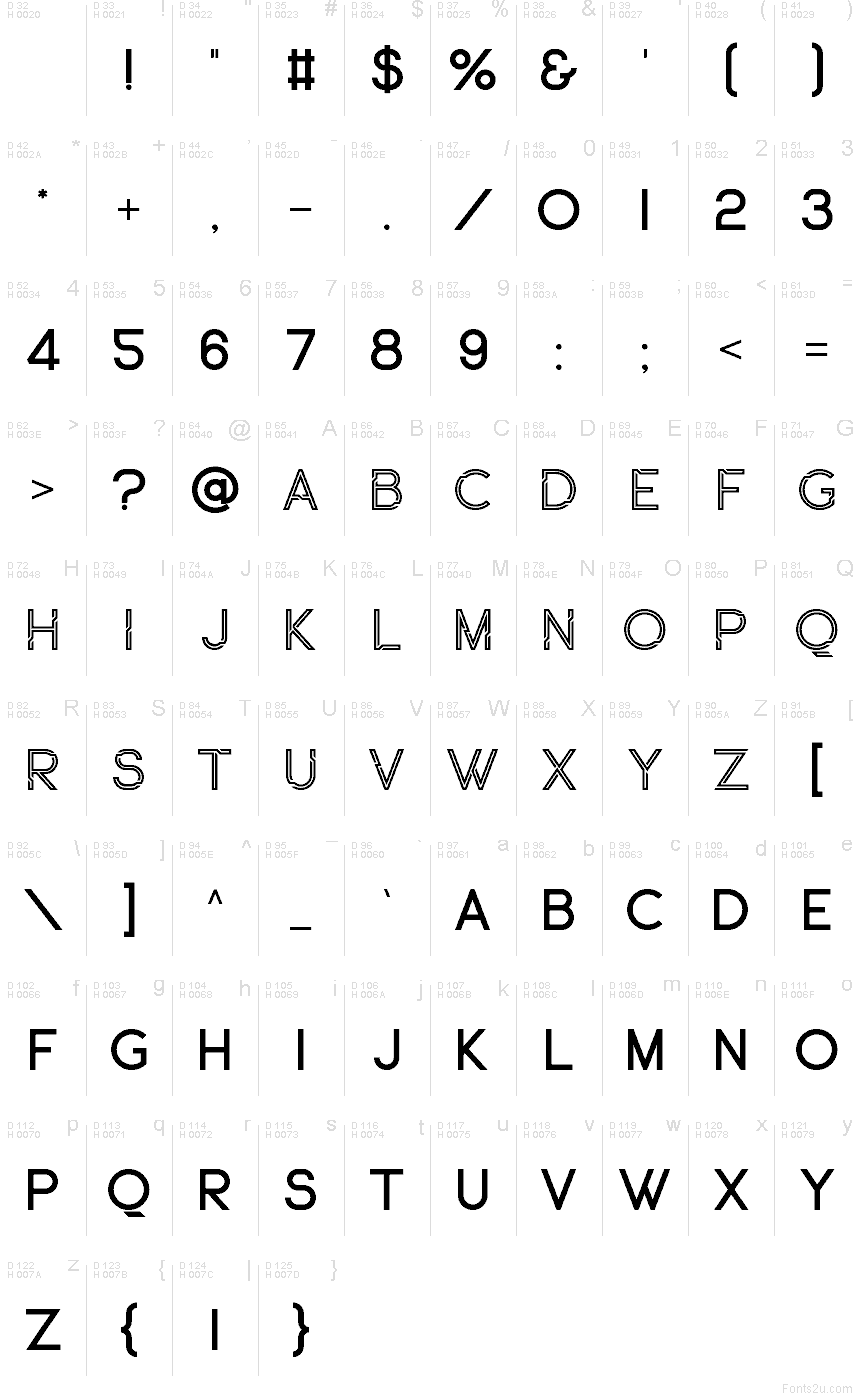
Orache, de ErmediaStudio, é uma fonte display moderna e gratuita com um visual geométrico e arquitetônico. Linhas paralelas desenham letras altas, com pequenos cortes diagonais que interrompem os contornos e formas triangulares nítidas que pontuam as curvas amplas.
Uma galeria de design contemporâneo poderia usar essa tipografia em cartazes de exposições, nos quais o traço preciso dialoga com desenhos de edifícios e objetos. Para uma marca de móveis, esses mesmos detalhes podem transformar a embalagem em uma extensão das linhas limpas e proporções medidas do produto. A arte visual para música eletrônica é outro cenário muito adequado, no qual as linhas interrompidas sugerem trilhas de circuitos na capa de um disco.